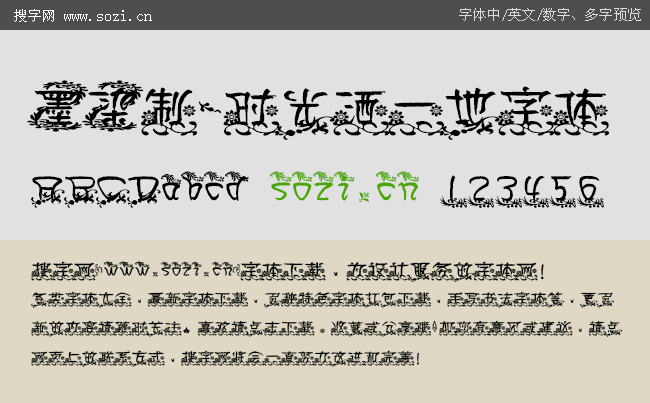
時光灑一地字體
搜字網(wǎng)給大家提供一款時光灑一地字體手機中文字體下載。時光灑一地字體是在漢儀陳頻破體周圍加上了一圈花紋圖案,漢儀陳頻破體結構新穎、風格獨特;呈倒梯形,筆畫的粗細富于變化,豎呈弧形,與字搭配協(xié)調(diào),并參入篆書的寫法;韻味十足。加入花紋后趣味性更強,非常適合喜歡個性的朋友在手機上安裝使用。